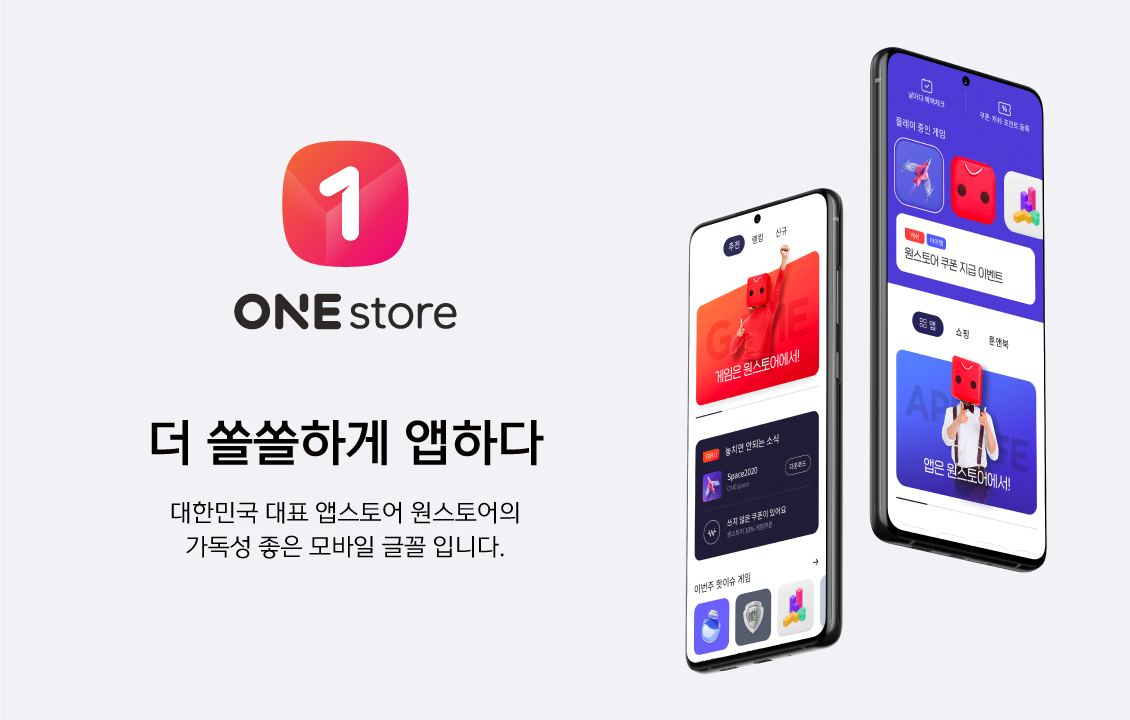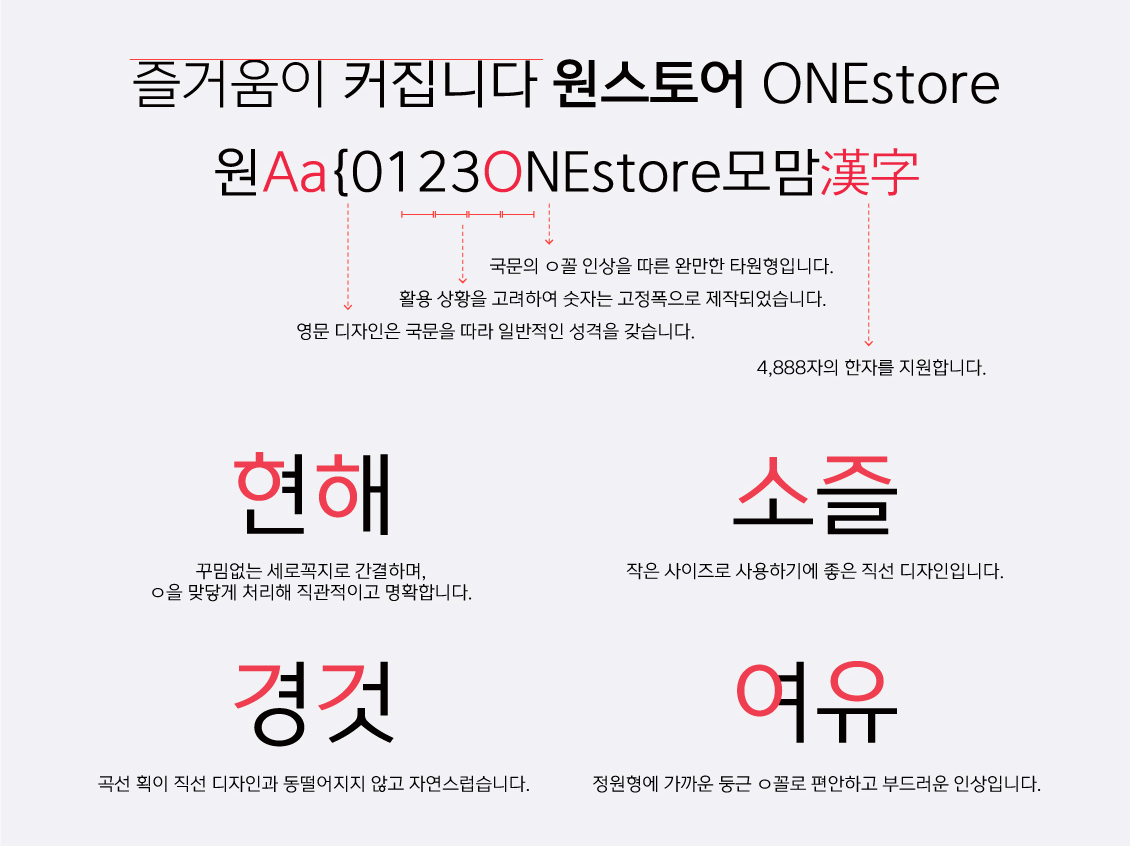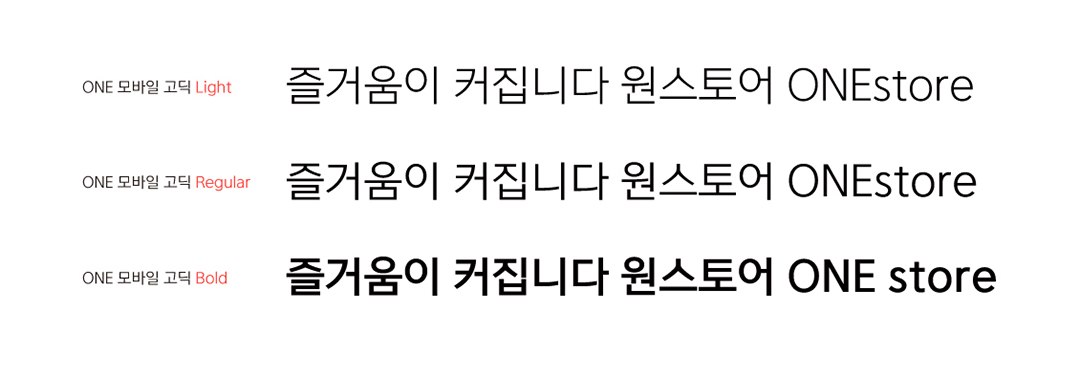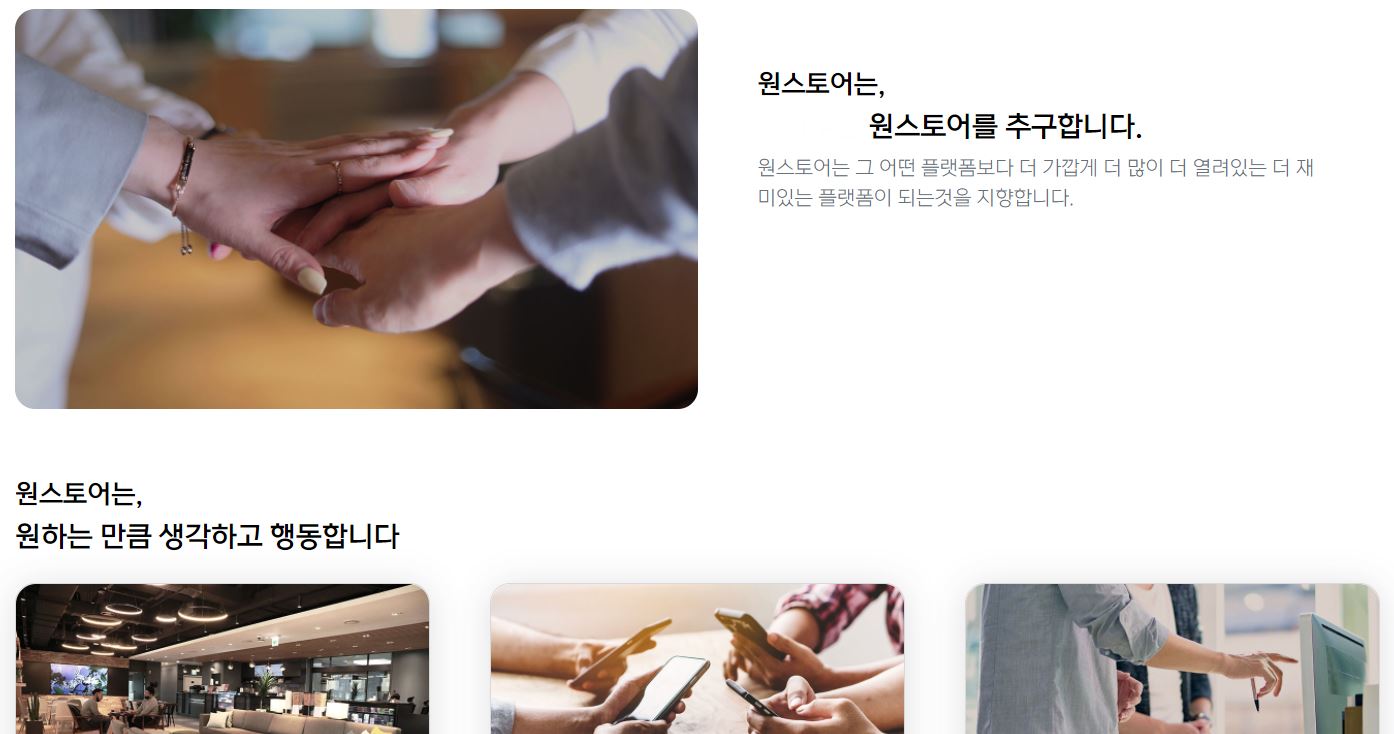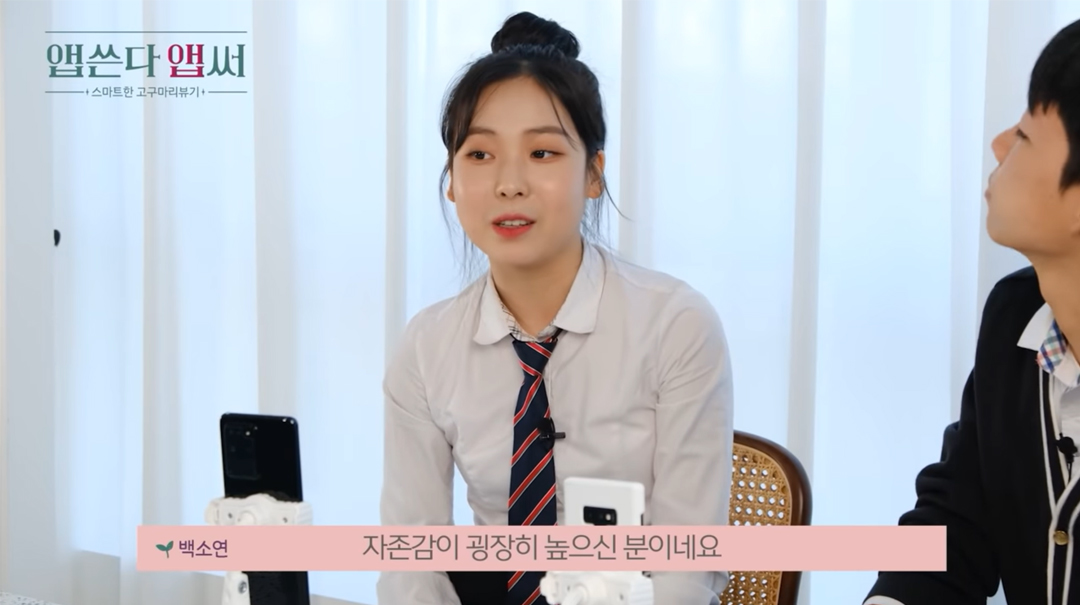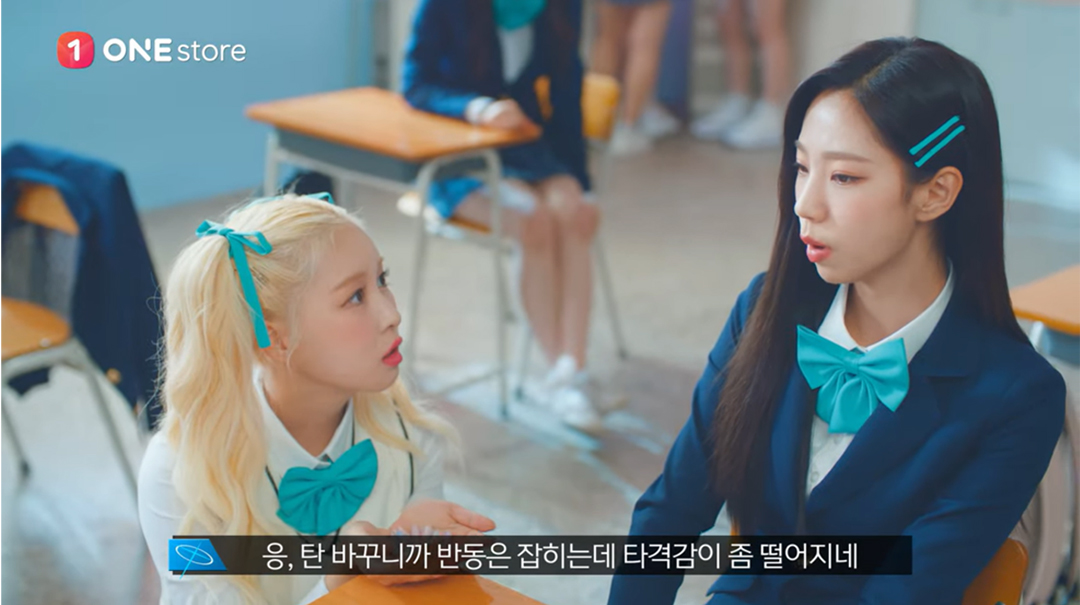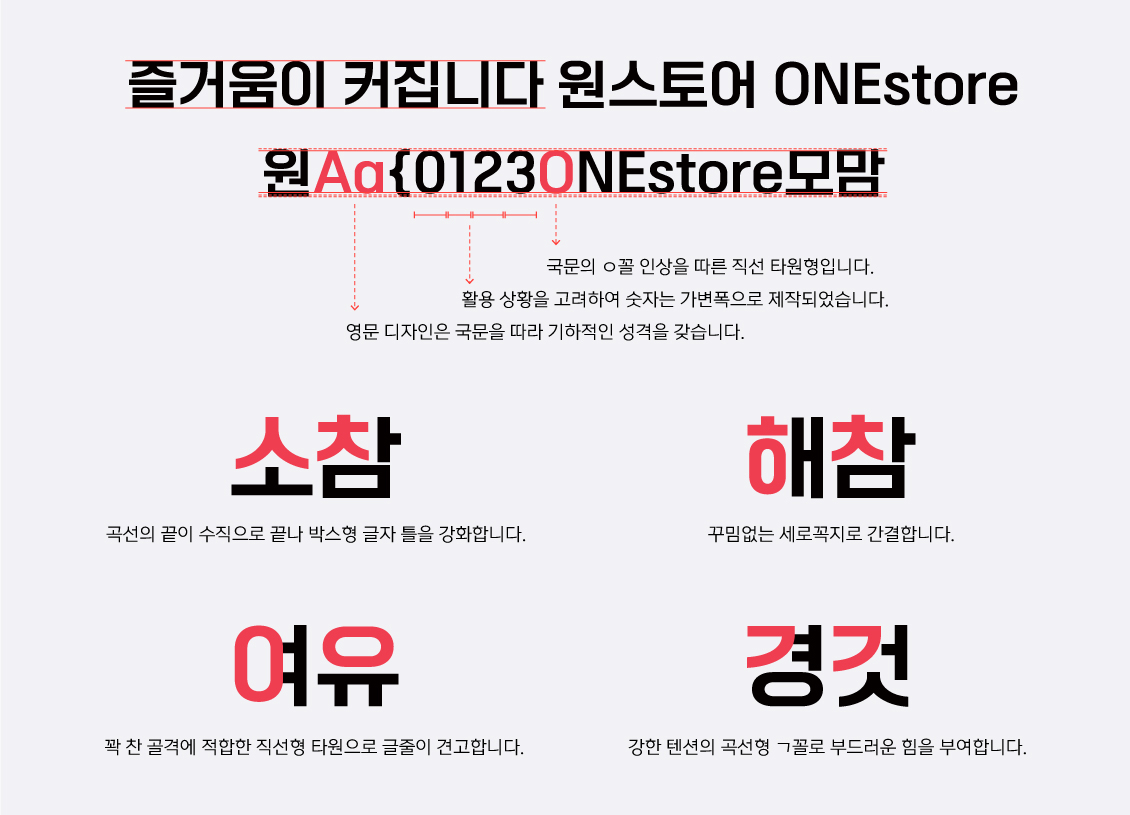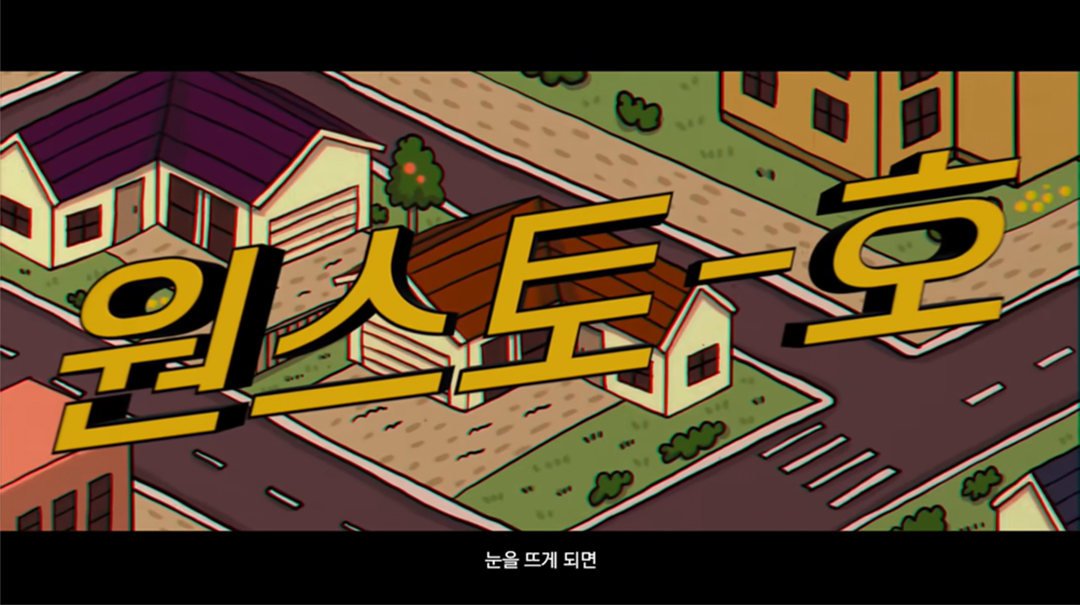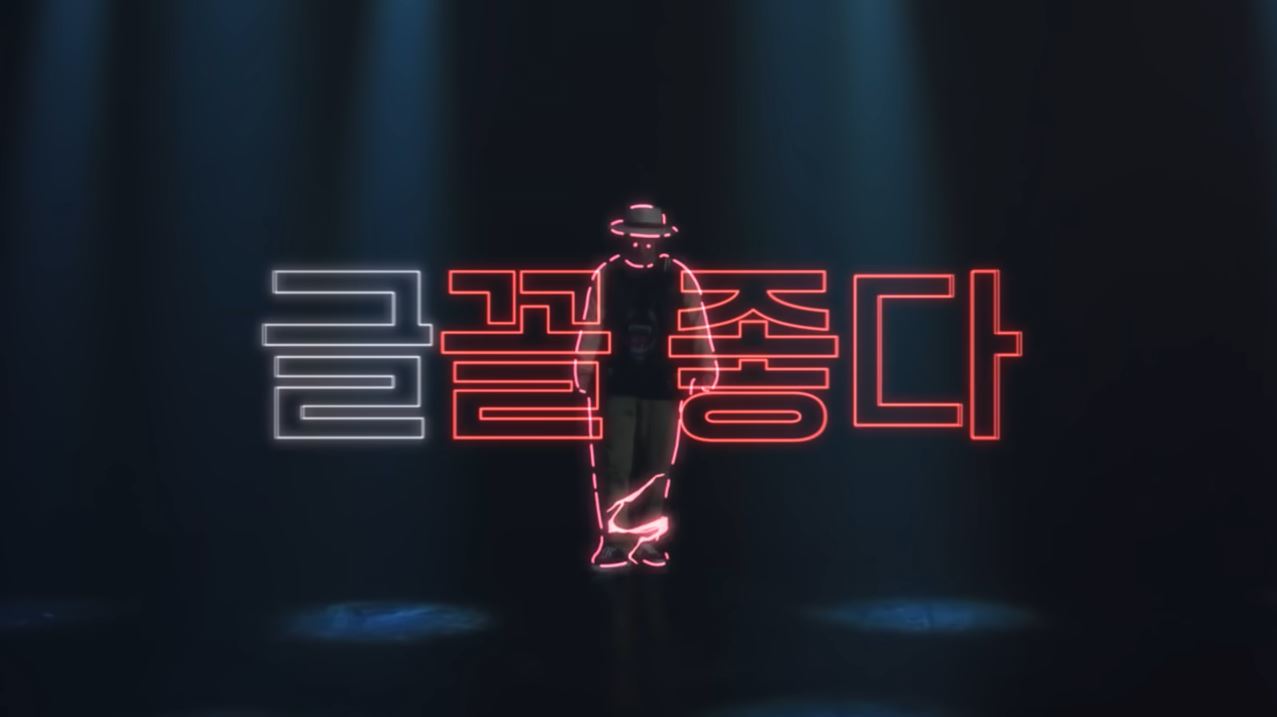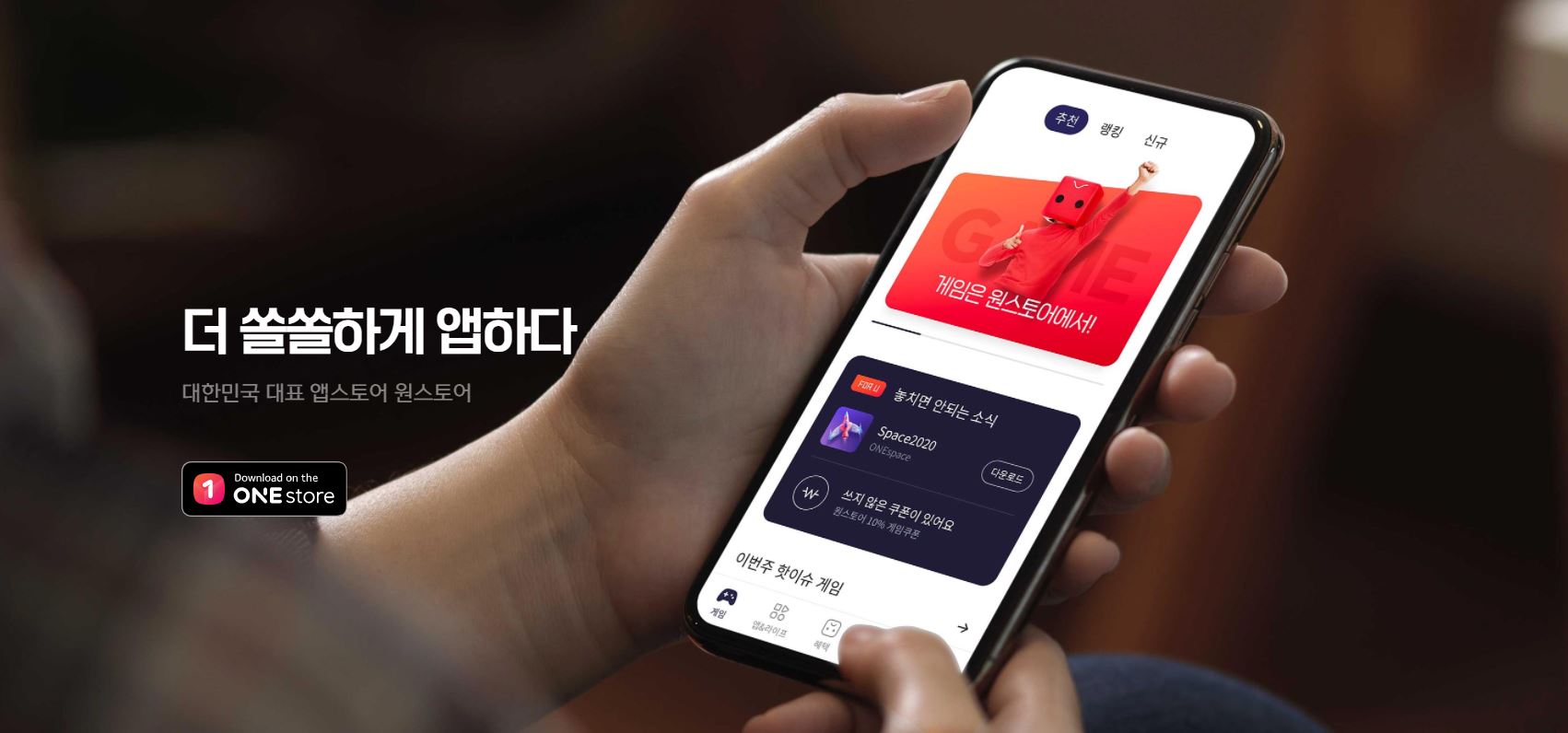
오늘 소개해드릴 전용서체는 대한민국을 대표하는 K-앱 마켓인 원스토어의 전용서체 「One 모바일」고딕체와 POP체 입니다. 원스토어는 대한민국 이동통신 3사(SK텔레콤, KT, LG U+)와 네이버가 함께 만든 앱 스토어로, 폰트릭스에서 2020년 후반부터 2021년까지 크게 3가지 스타일의 원스토어 전용서체를 개발, 제작했습니다.
모바일에서의 사용이 많은 점을 고려해 가독성이 최적화된 본문용 고딕체, 트렌드를 반영한 꽉 찬 네모꼴의 제목용 고딕체, 그리고 생동감 있고 귀여운 손글씨 느낌의 POP체까지 기업의 니즈와 컨셉에 부합하는 글꼴들을 제작했습니다. 각각의 매력이 돋보이는 원스토어 전용서체들을 만나보세요.
편안하고 모던한, ONE 모바일고딕 본문체
가독성에 중점을 두어 제작한 고딕 본문체는 맑은 고딕보다 좀 더 여백을 줄여 보기에 편안하고 안정적인 느낌이 들도록 제작했습니다. 모던하면서도 깔끔한 인상의 자소 디자인, 안정적인 글줄로 읽기에 편안한 글꼴입니다.
본문용 고딕체는 Light, Regular, Bold 총 3가지 굵기로 파생되어 더 높은 사용성을 갖고 있으며, 단단한 골격 형태로 무게 중심이 잘 잡혀있어 다양한 환경에 적합합니다.
이렇게 홈페이지 내 텍스트가 필요한 부분, 공식 유튜브 채널의 자막 등 여러 방면으로 활용되고 있습니다. 가독성도 뛰어나지만 기존의 본문용 서체와는 차별화된 디자인이 원스토어만의 스타일을 보여줍니다.
Back to Basic, ONE 모바일고딕 제목체
단단한 힘이 느껴지는, 기본에 충실한 제목용 서체입니다. 'ㅇ'꼴이 꽉 찬 골격에 적합하게 직선형 타원 형태로 제작된 특징이 있으며, 국문 스타일에 맞춰 영문과 숫자 디자인도 세심하게 제작했습니다.
디자인 자체가 화려하진 않지만 베이직한 힘이 있어 타이틀로 썼을 때 눈길을 끌 수 있습니다. 유튜브 썸네일이나 강조하는 문구, 홈페이지 등에 다양하게 활용되고 있으며, 두께가 굵고 직선적인 획이 깔끔하고 안정적인 느낌을 주는 서체입니다.
귀엽고 발랄한 ONE 모바일 POP체
손글씨 획순을 살린 자소 형태와 가분수 스타일의 발랄한 글꼴 POP체입니다. 통통 튀는 게임 속 캐릭터처럼 귀여운 모습을 형상화했는데요~ 리드미컬한 글줄과 강약 있는 굵기가 매력을 더합니다.
캐주얼하고 발랄한 서체 스타일이 매력적인 폰트로 게임 속 효과를 주는 문구나 유튜브 자막으로 활용되고 있습니다.
원스토어 전용서체는 본문체 3종, 제목체와 POP체까지 총 5가지 서체를 한글 11,172자 / 한자 4,488자 / 심볼 986자로 개발하고 제작한 큰 프로젝트였습니다. 고객과의 커뮤니케이션과 경험을 중시하는 기업과 전문적인 서체 개발의 노하우와 기술력이 만나 좋은 성공 사례를 만들었습니다. 전용서체 개발은 브랜드의 힘을 키우고 더 나아가 좋은 이미지를 구축하는데 큰 도움이 됩니다. 완성도 높은 서체로 타이포 브랜딩 효과를 경험해 보세요!